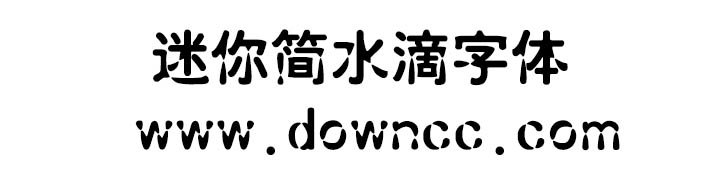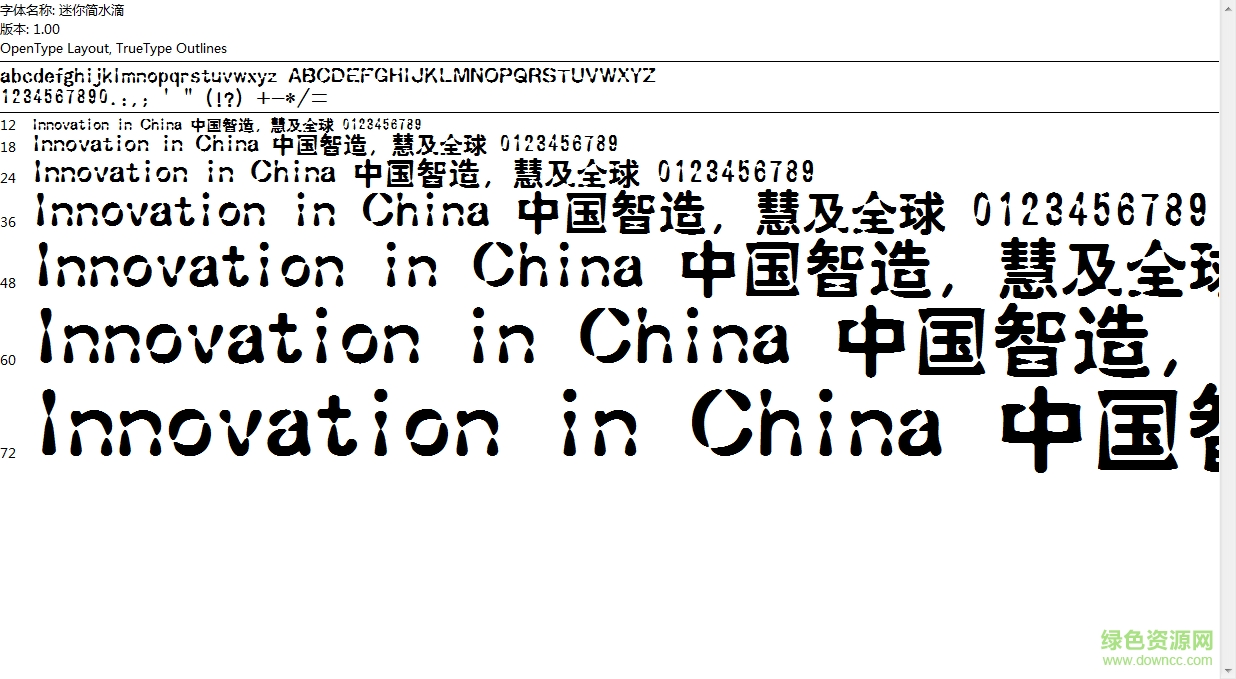
迷你簡水滴是一款端莊美觀的win字體,采用粗線字體,整體形象非常出色,可以直接導(dǎo)入至ps中,廣泛的應(yīng)用于廣告設(shè)計、平面設(shè)計、動漫設(shè)計等領(lǐng)域,喜歡的朋友歡迎來綠色資源網(wǎng)下載!
迷你簡水滴整體給人一種大氣的感受,就如水滴版好看,每一筆都有那么一點點粗,是很多地方都在使用的字體